Die britische Creative Review widmet sich heute dem überarbeiteten Verpackungsdesign der weltweit vertriebenen Nivea-Kosmetik-Produkte und titelt spöttisch: »A cleaner, simpler N IVEA«. Dabei spielt der Autor Patrick Burgoyne auf den miserabel spationierten NIVEA-Schriftzug an, der seit einigen Jahren im Einsatz ist – mit einem auffällig weiten Abstand zwischen dem ersten und zweiten Buchstaben. Allerdings war die Logotype gar nicht Gegenstand des Redesigns, wie gestern bereits ein Kommentator im Designtagebuch treffend vermerkte. Und das ist schade, wäre doch die Überarbeitung von Fuseproject der ideale Zeitpunkt für die Behebung dieses Uraltfehlers.
Vertraut man der Nivea-Markenhistorie auf Pinterest, wurde der falsche Buchstabenabstand (er betrifft nicht nur N und I, sondern alle 5 Buchstaben) vor 20 Jahren eingeführt. Anfang 2000 bekam der Schriftentwerfer Achaz Prinz Reuss von Beiersdorf den Auftrag, aus dem Nivea-Logo eine komplette, eigenständige Schrift zu entwerfen. Ende 2000 schloss er die Arbeit ab. Ausgehend von der Kompromiss-Hauschrift Metro Black von William A. Dwiggins aus den 30er Jahren hatte Reuss eine Schriftfamilie mit zwölf Schnitten sowie eine Textversion erstellt. Seitdem wird für die Marke zur Identitätssteigerung ausschließlich dieser Zeichensatz verwendet, von der Korrespondenz über die Printanzeigen oder Fließtexte bis zur Verpackung – natürlich auch im Ausland, unter anderem mit den passenden kyrillischen und griechischen Zeichen.
Dass der Schriftentwerfer wahrscheinlich nicht für die Spationierung des Logos verantwortlich ist, verrät ein Blick auf die aktuelle Website. Dort zeigt sich die Nivea Bold in Überschriften – als Webfont, harmonisch spationiert – in Bestform:
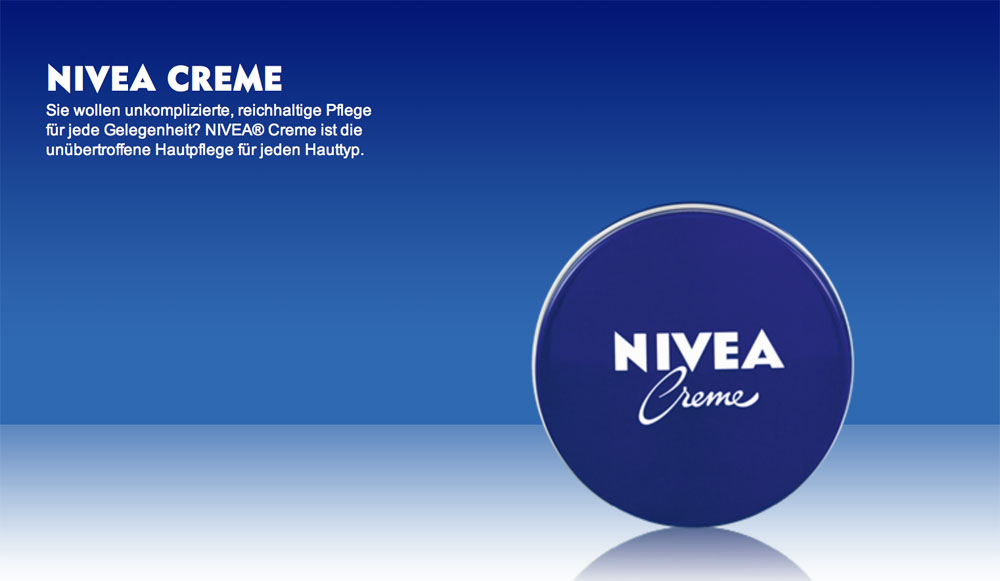
So falsch finde ich das Original nicht. Wenn man sich die Zwischenräume anguckt – was man ja beim Spationieren vor allem tut – ist das Original für meine Augen näher am Ideal als die »korrigierte« Version. Das Grundproblem ist natürlich, dass V und A extrem breit sind und dadurch riesige Lücken klaffen lassen. Und das könnte man wohl am besten durch insgesamt luftigere Spationierung ausgleichen.
Ich auch. Ich habe den Schriftzug nicht verstanden, bis ich angefangen hatte Design zu studieren und das mit der Spationierung anzuwenden. Da kann ich mich nur den Vorrednern anschließen.
Meiner Meinung nach war die 1970er-Version (siehe Seite 48 in der neuen PAGE-Ausgabe) so ziemlich perfekt.
Der Verdacht liegt nahe, dass wir uns in den letzten 20 Jahren an die Lücke gewöhnt haben. Mir ist sie bisher auch nicht ins Auge gesprungen … erst jetzt, als ich das Redesign genauer unter die Lupe genommen habe.
Ich denke dass die korrigierte Version besser aussieht. Beim Spationieren ausschließlich die Zwischenräume zu beachten macht nur bei Textschriften Sinn. Umso größer und kompakter die Schrift wird, umso mehr spielen die Abstände eine Rolle. Bei einem Schriftzug muss man immer einen Mittelweg zwischen Zwischenräume und absolute Abstände finden. Man kann einen Schriftzug grundsätzlich nicht wie eine Textschrift behandeln. Als jemand, der sowohl Textschriften entwirft als auch Logotypes, mache ich diese Erfahrung ständig.
Ich finde das Original besser, da hier die großen Flächen (Dreiecke) ein optimales Gegenstück haben. In der korrigierten Version bekommen diese zu viel Gewicht.
Also wenn ich Wikipedia glauben darf
ist das NI-Kerning seit 1949 kaputt…
Aber irgendwie sind auch Produkte mit “korrigiertem” Logo im Umlauf (gewesen).
Also in einem Punkt gebe ich Euch auf jeden Fall Recht. Es fällt tatsächlich nicht so sehr auf – ist mir noch nie aufgefallen! Aber wenn man es genau nimmt ist die korriegierte Variante tatsächlich wesentlich besser. Die Faustregel beim Spationieren ist ja schließlich: Nimm drei Buchstaben und der in der Zweite muss optisch mittig sitzen. Das tut das “I” definitiv nicht – tendiert eindeutig zum “V”… Ich plediere ganz klar für die optimierte Version!
@ Jörg Schmitt
Diese Faustregel gilt nur für das schrittweise Ausgleichen von Buchstabenpaaren. Da man ein Wort/eine Wortmarke aber im Gesamten betrachtet und nicht in dreiteiligen Buchstabengruppen, muss am Ende immer das Wort im Ganzen auf sein optisches Gleichgewicht überprüft werden. Es nützt also nix, wenn man sich das N-I-V herausgreift und dann dann das gesamte Wort danach bewertet.
Ich denke, dass es für das Nivea-Logo von Vorteil wäre, wenn es für verschiedene Abbildungsggrößen optimiert wäre. In kleinen Größen scheint mir der Ausgleich im Originallogo passend, bei größeren Abbildungsgrößen tendiere ich zur »korrigierten« Version.
@ Jörg Schmitt
Wollte auch das gleiche wie mein Vorredner sagen, dass das ganze Wort zu beachten ist. Und da ist es für mich mit der neuen Version nicht sehr gelungen, aber naja, das wird sich so oder so in die Köpfe brennen und vielleicht fällt das dann gar nicht mehr so sehr auf.
Wo haben der Autor dieser Kritik und Patrick Burgoyne denn den Umgang mit Typografie gelernt? Jeder gelernte Typograf weiss doch, dass das Ausgleichen von Zwischenräumen zur Grundausbildung gehört und dass man sich dabei an den grössten (unvermeidichen) Zwischenräumen zu orientieren hat (das »Licht« zwischen den Buchstaben). Keine Ahnung, wonach sich der geringe Abstand N I in der korrigierten Version orientiert (sieht eher nach der Arbeit einer Tippse aus, die nur Buchstaben nebeneinanderklopft). Jedenfalls ging hier das Gefühl für Figur-Grund-Relationen der Buchstaben und deren Zwischenräumen verloren. Die sogenannte »Lücke« ist keine Lücke, sondern die notwendige Konsequenz, die vom V schon vorgegeben wird, wenn der Abstand ausgeglichen werden soll.